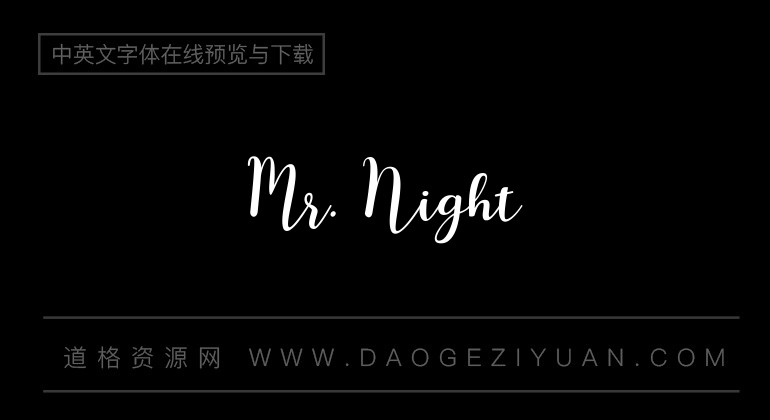
Mr. Night是一款由FontFabric字体工作室设计的手写体字体,具有独特的曲线和自然的笔触,适用于创意设计和品牌标识。它的设计特点是柔和的曲线,可以提供给设计师更多的创意空间,可以创造出更加有趣的设计效果。它可以支持多种语言,可以用于商业、网页、Logo等设计项目中。内容介绍
Mr. Night是一款非常不错的手写艺术字体,具有很好的视觉感,适合于文化类的宣传设计、商业类品牌的广告和产品包装设计以及个性化文字排版等较多场景。